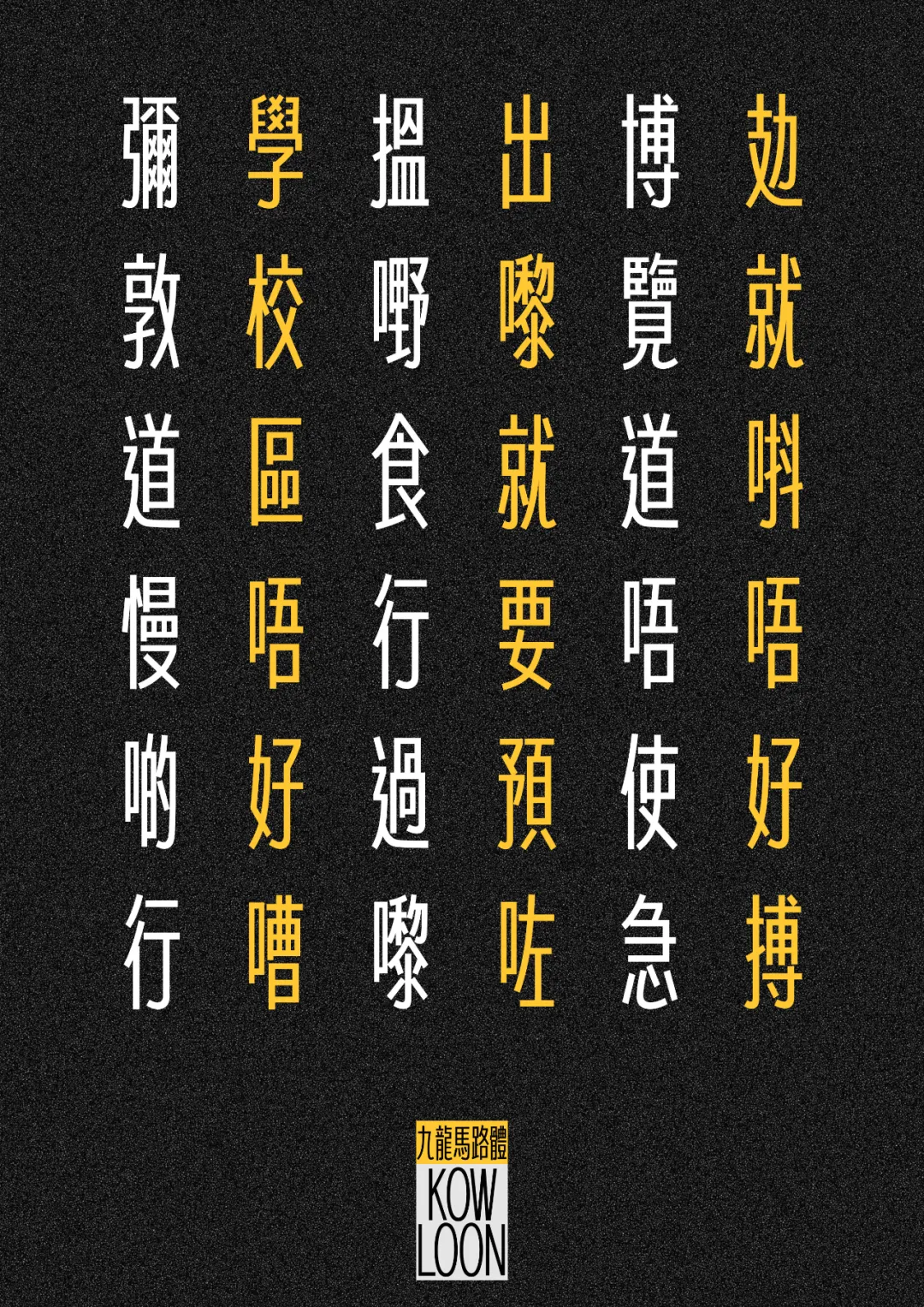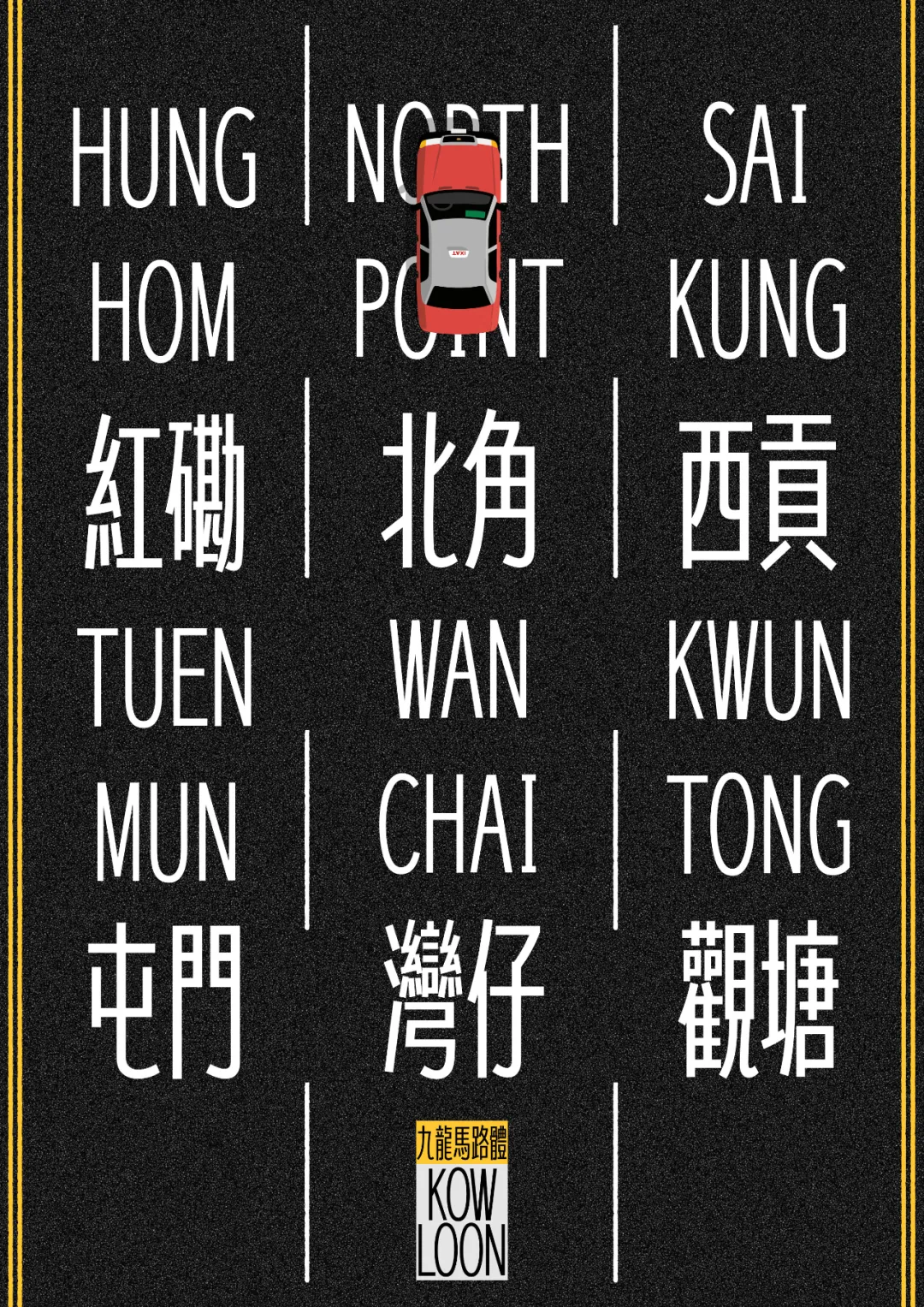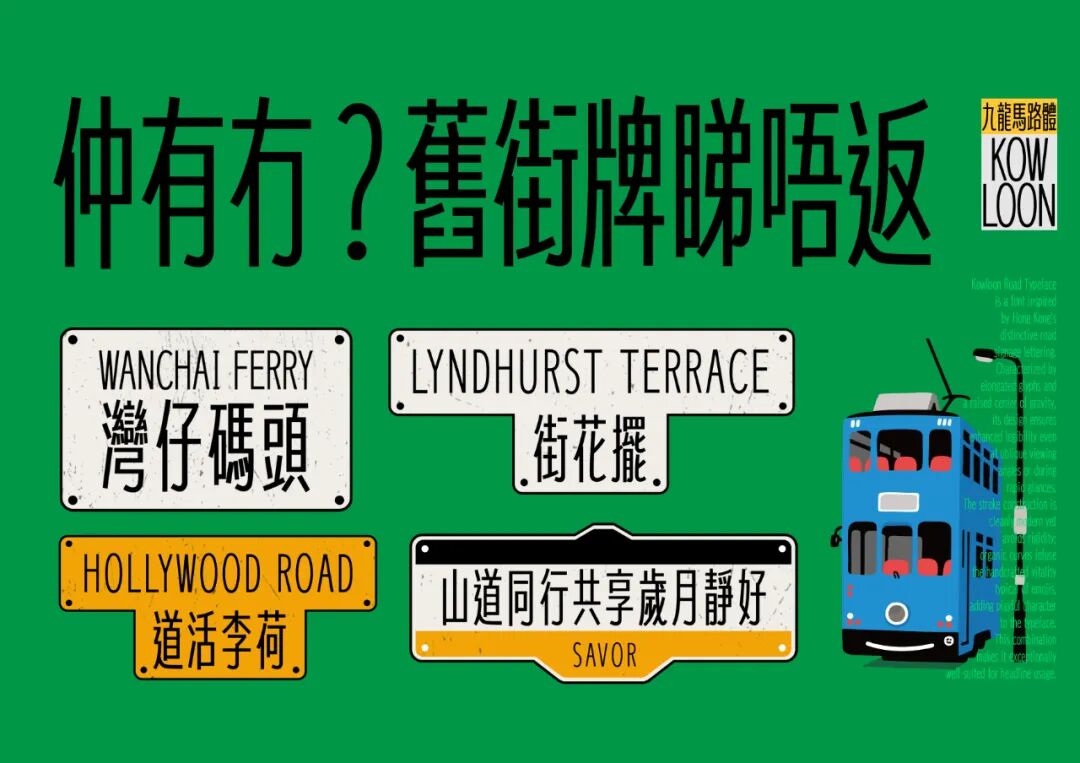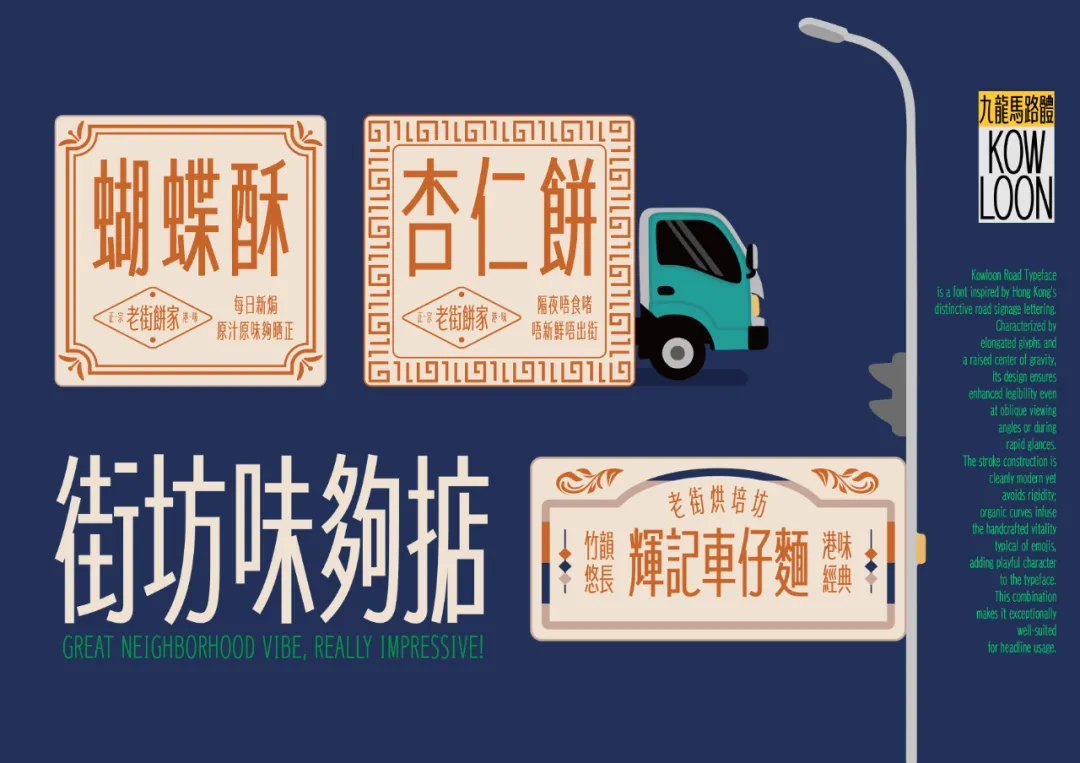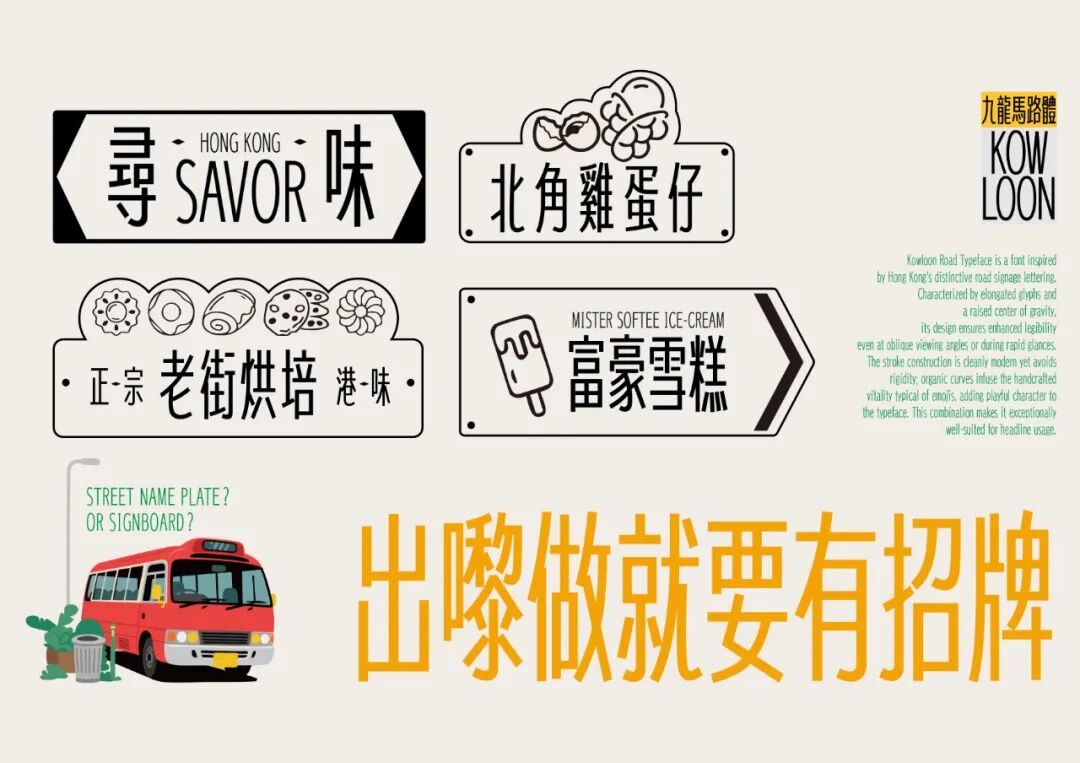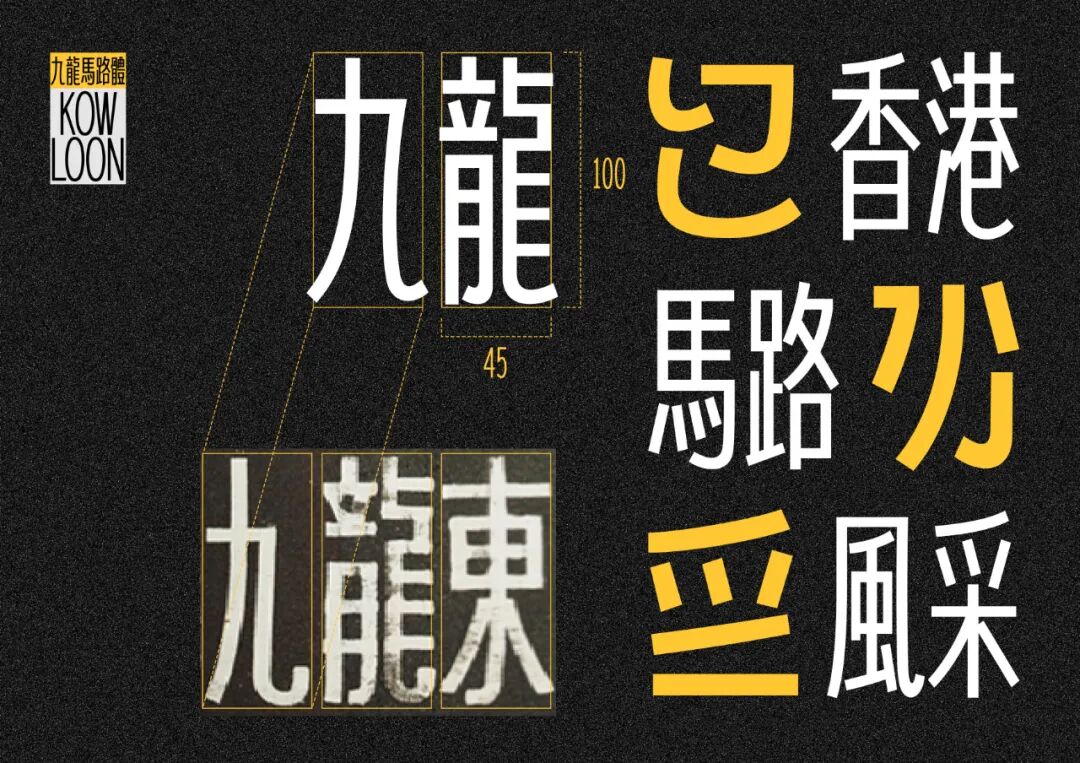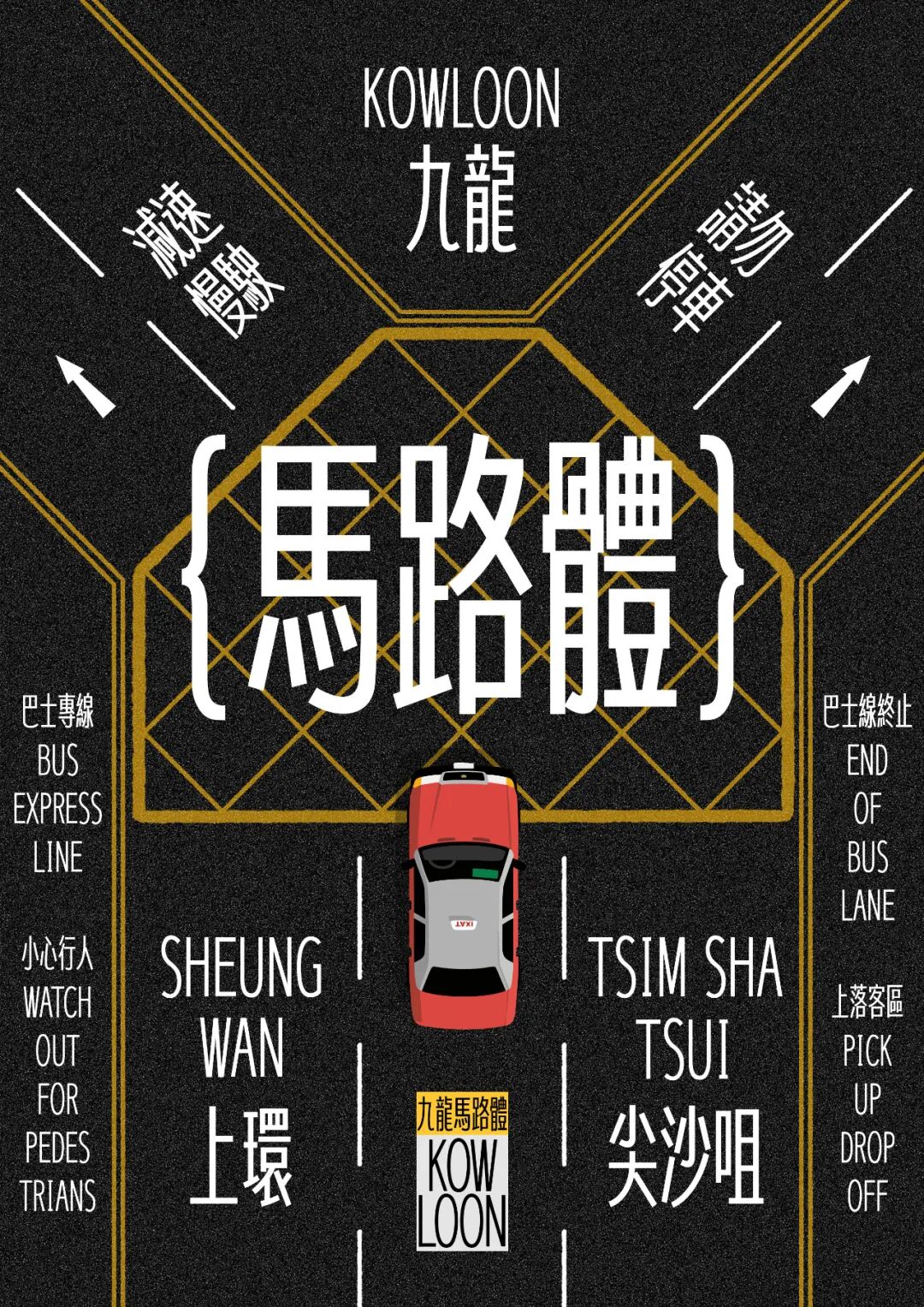
藏在天橋底的港字文化!“NICETYPE九龍馬路體” 讓城市記憶活在文字裏
“NICETYPE九龍馬路體”的靈感深深植根於香港獨特的街頭視覺遺產——那些散落在天橋底、街角處的手繪馬路標識。這些字體不僅是城市高效運轉的基石,更是香港草根智慧與生猛美學的結晶。
為適應高速行車時的瞬間識讀,其修長體態、加高重心和簡練筆畫意外鑄就了極高的視覺辨識度與衝擊力;不拘一格的手工筆觸更散發着靈活、務實的本土精神與濃厚的生活温度。
我們從這一承載城市集體記憶的公共符號中汲取精髓,以現代設計語言進行重構。字體延續了高重心和修長的核心結構,確保在快速斜視或遠距離觀看時依然清晰易讀,解決了標題字體的功能性痛點。
同時,筆畫設計化繁為簡,卻在關鍵轉折處巧妙融入了帶有手繪活力的曲線,猶如馬路字的人文氣息與繪文字的俏皮質感在此交融,賦予嚴謹的骨架以自然流暢的呼吸感與獨特趣味,徹底打破了現代字體易流於冰冷機械的窠臼。這是一次對本土視覺基因的深度解碼與創造性再生。
“NICETYPE九龍馬路體”天然契合香港高密度信息環境的需求,尤其在需要快速抓取眼球、傳遞文化活力與本土情感的領域——如標題、海報、文創產品、品牌標識及導視系統——它能強勢突圍,精準傳達信息並激起觀者的在地共鳴。
選擇“NICETYPE九龍馬路體”,即是選擇使用一種紮根於鬧市煙火、飽含集體記憶的視覺方言來講述當代香港故事,讓設計承載歷史,使文字煥發新生,向世界自信展示本土文化基因在數字時代的蓬勃可能——根在鬧市,字觀天下。